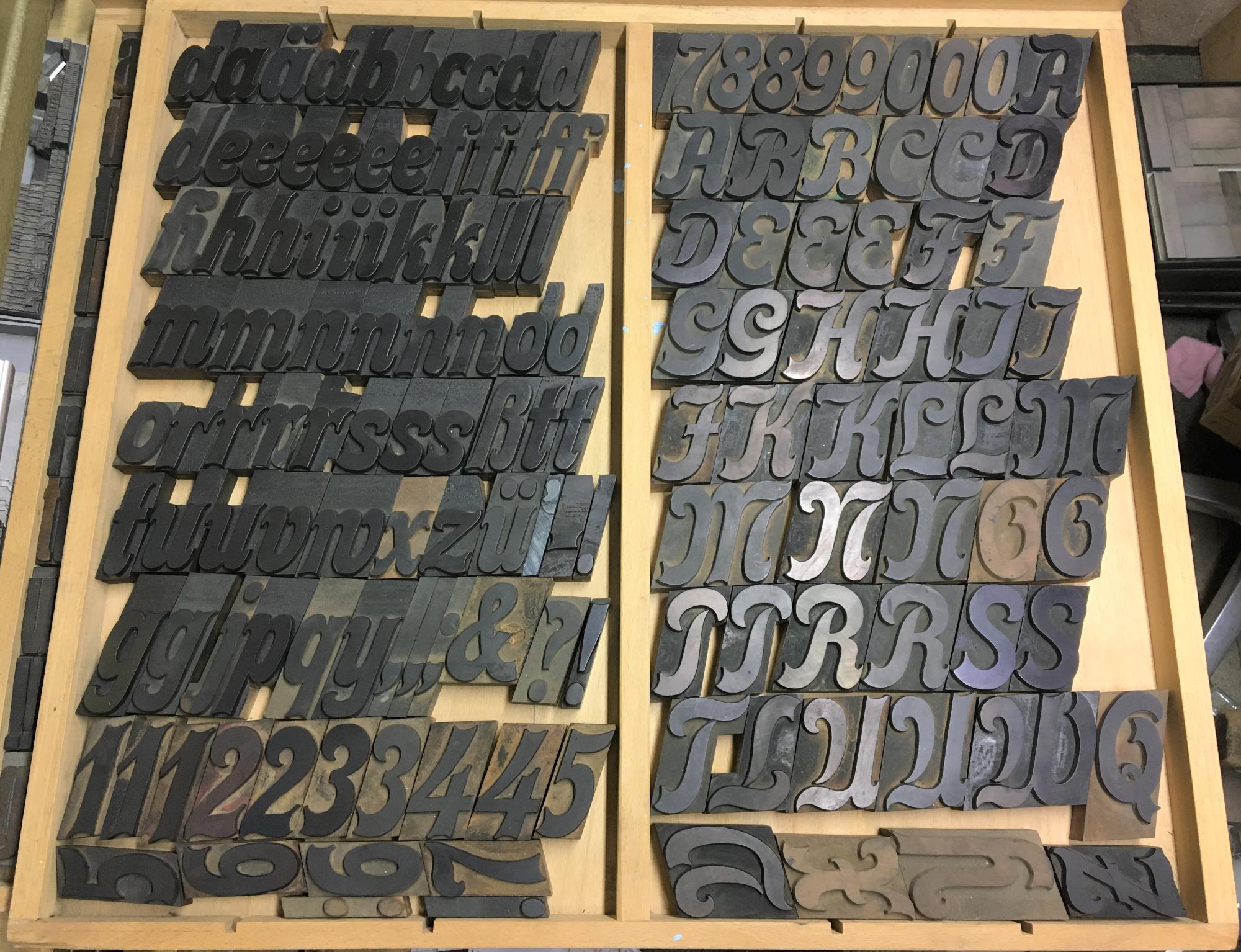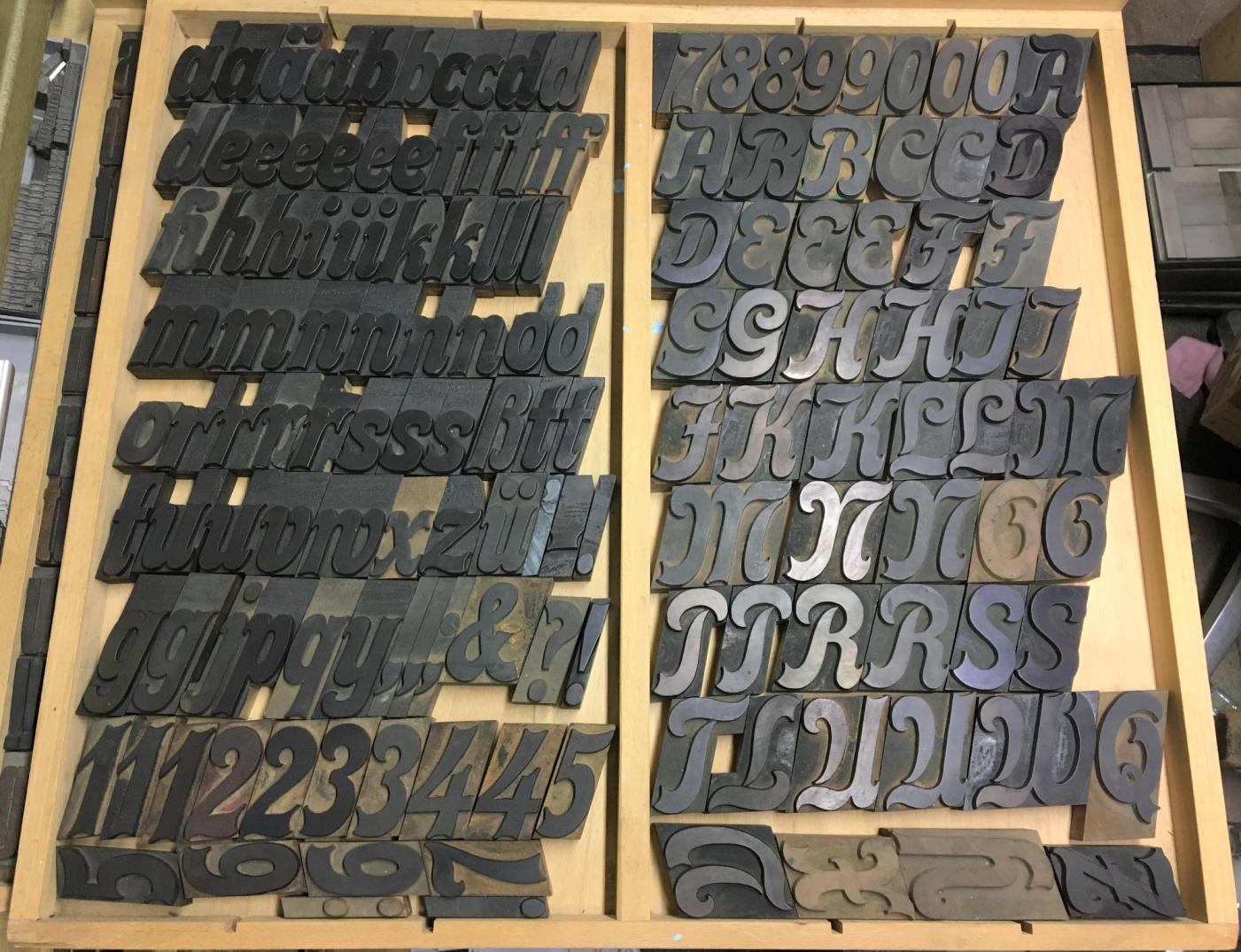
Holzlettern identifizieren
die Schrift auf dem nachfolgenden Foto ist kürzlich zu unserer Sammlung gekommen. Auf den ersten Blick für die "Belvedere" gehalten stimmt dies leider nicht. Der Entstehungszeitpunkt der Schrift dürfte zwischen 1895 bis 1930 sein. Vielleicht hat jemand in irgendeinem Schriftmusterbuch diese Schrift schon einmal gesehen und kann mit Namen oder Nummer sowie der Schriftgießerei bzw. Holzletternmanufaktur weiterhelfen. Besten Dank!